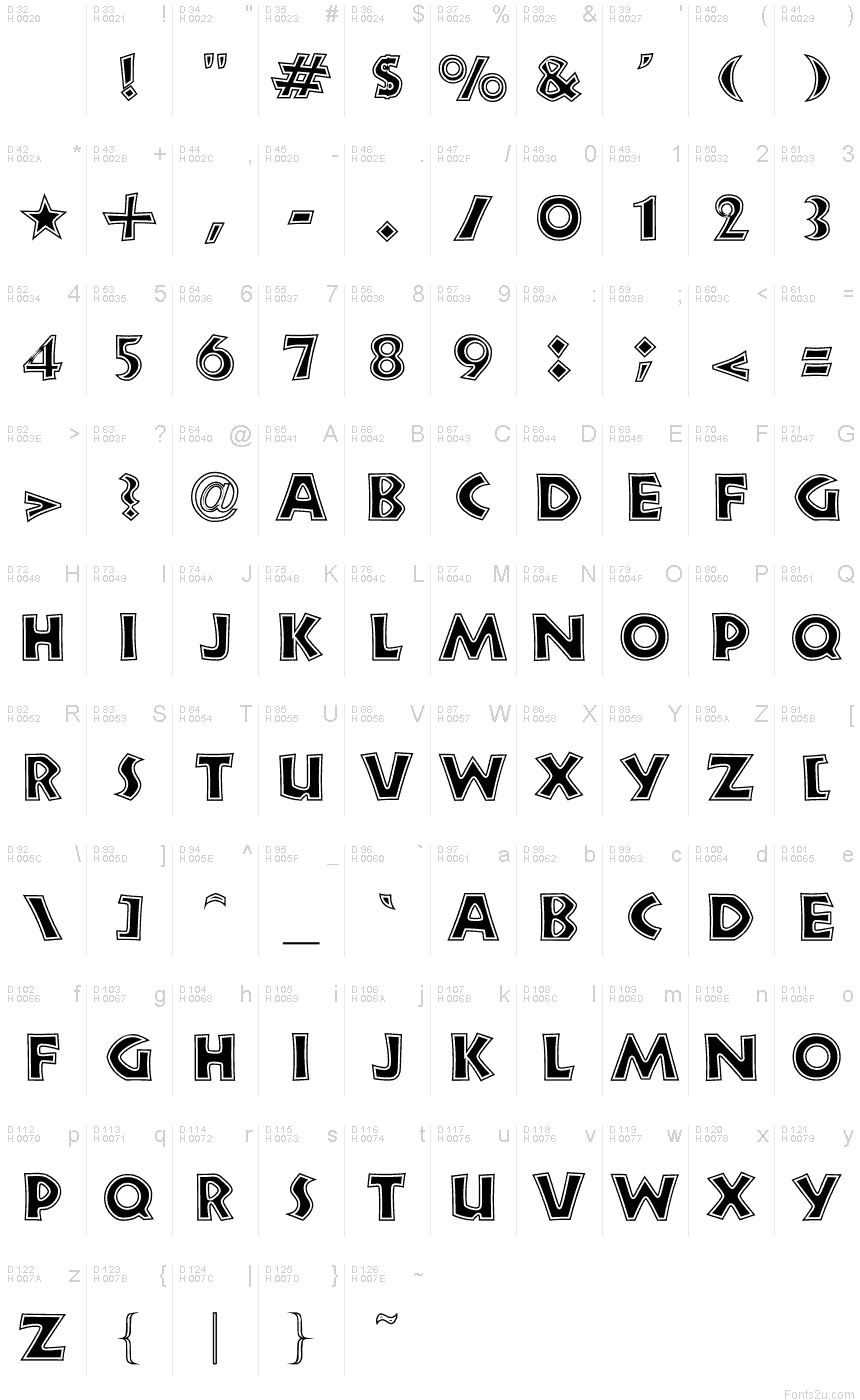
New Land Contour, darmowy krój pisma retro typu display od Jonathana Smitha, przekształca proste litery blokowe w warstwowy styl przypominający malowane szyldy, z ciemnym rdzeniem, wąskim wewnętrznym obrysem i dodatkową zewnętrzną krawędzią. Ten powtarzający się zabieg konturowy nadaje alfabetowi plakatową sylwetkę i sprawia, że wygląda on niemal jak wycięty ręcznie, unikając przy tym zwykłego, geometrycznego wyglądu.
Krój ten świetnie sprawdzi się na menu w barach, opakowaniach w stylu vintage, plakatach wydarzeń, grafikach nawiązujących do gier arcade oraz nagłówkach witryn sklepowych, gdzie podwójna krawędź pozwala wyraźnie obramować krótkie słowa. Ponieważ to właśnie kontury wykonują większość pracy wizualnej, New Land Contour doskonale nadaje się również do odznak i logotypów, które wymagają klimatu starych szyldów bez konieczności stosowania efektów postarzania.